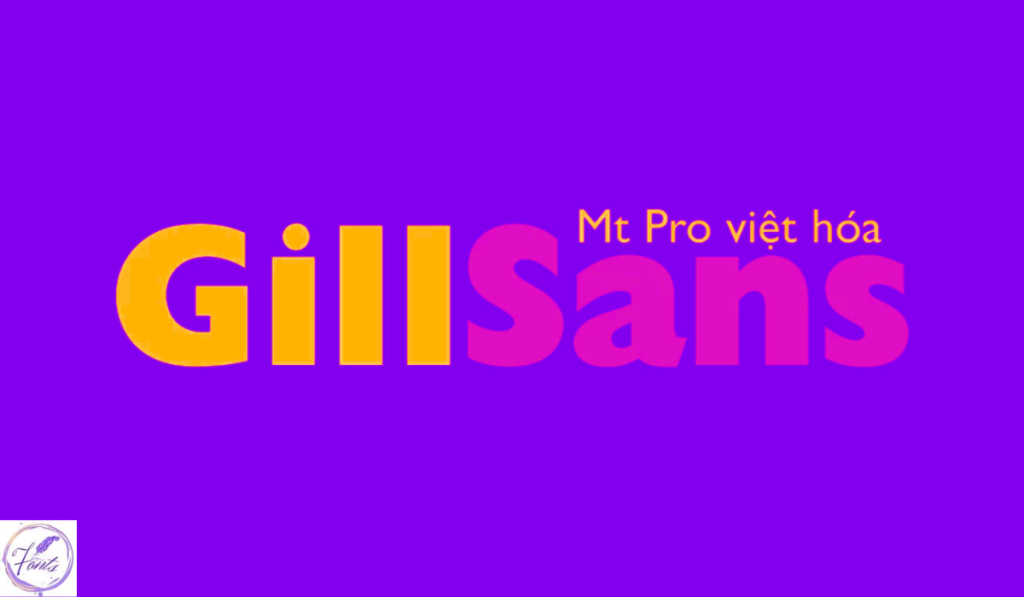
Font Gill Sans việt hóa
Tác giả: Eric Gill
Ngày phát hành: 1928
Bộ Font: Gill Sans
Phân loại: Cá tính, độc đáo
Kiểu chữ: Sans-serif (không chân)
Độ dày: Thin, ExtraLight, Light, Regular, Medium, SemiBold, Bold, ExtraBold, Black, Condensed, nhiều độ dày khác nhau
Font gill sans việt hóa là một trong những bộ font nổi tiếng và được sử dụng rộng rãi nhất hiện nay. Được thiết kế bởi nhà thiết kế Eric Gill vào năm 1928, font này mang lại sự kết hợp hoàn hảo giữa nét cổ điển và hiện đại.